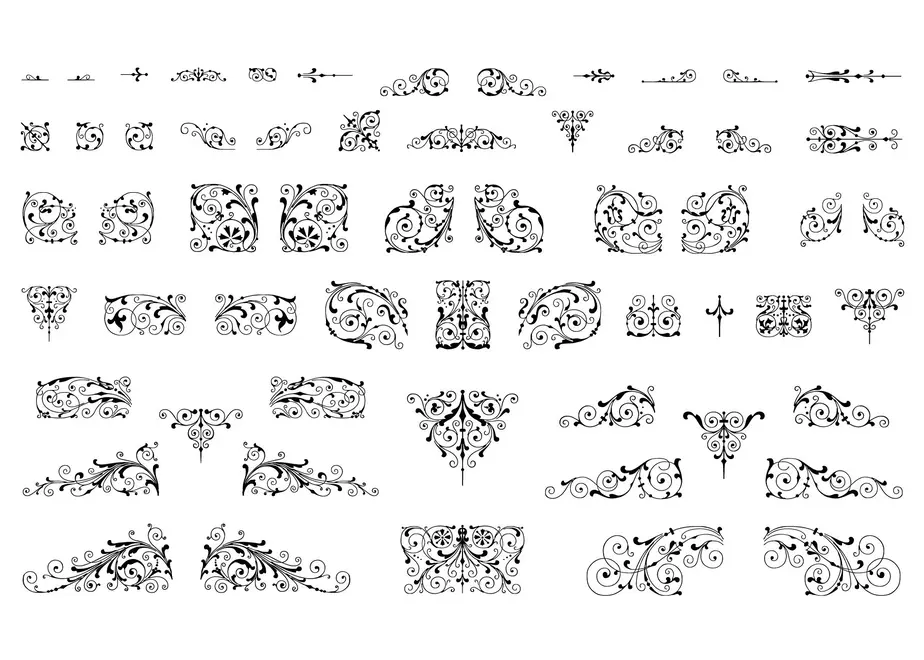
装飾活字:PRINTERS'FLOWERS joh. enschede en zoen te haarlem(物理加工の為の)
The Enschede type foundry's flower-shaped decorative type series 60 has been redesigned for physical processing. This is the data outlined by Adobe Illustrator (Irare ver10, .ai).
■ Product overview
59 differently shaped objects, all outlined
エンスヘデ活字鋳造所による花形装飾活字シリーズ60を物理加工用に設計から作り直しました。アドビイラストレーターにてアウトライン化した(イラレver10,.ai)のデータです。
■商品概要
全てがアウトライン化された59個の形の違うオブジェクト